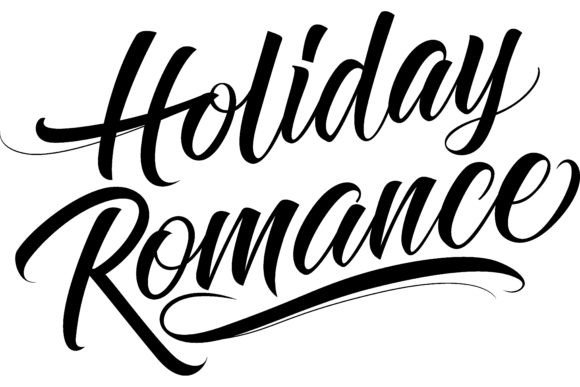
Holiday Romance Lettering. Calligraphic
Holiday Romance Lettering – A Elegância da Caligrafia em Cada Traço
Se você procura transformar cartões de Natal, pôsteres festivos ou mensagens íntimas em verdadeiras obras‑de‑arte, o Holiday Romance Lettering chega como a escolha perfeita. Esta tipografia caligráfica combina o charme romântico com a delicadeza das letras manuscritas, trazendo um toque pessoal e sofisticado a qualquer projeto de fim de ano.
- Estilo único: Cada caractere foi desenhado à mão, oferecendo variações sutis de espessura que imitam a escrita tradicional com pena.
- Versatilidade criativa: Ideal para cartões de felicitações, convites de festas, posters comemorativos e mensagens privadas que precisam de um ar de intimidade.
- Leitura fluida: Apesar da estética ornamental, a fonte mantém excelente legibilidade, essencial para textos curtos e longos.
Com Holiday Romance Lettering, cada saudação ganha personalidade própria, evocando o espírito caloroso das festas e o afeto de quem escreve. Experimente hoje mesmo e sinta a diferença que uma caligrafia autêntica pode fazer nas suas criações natalinas!